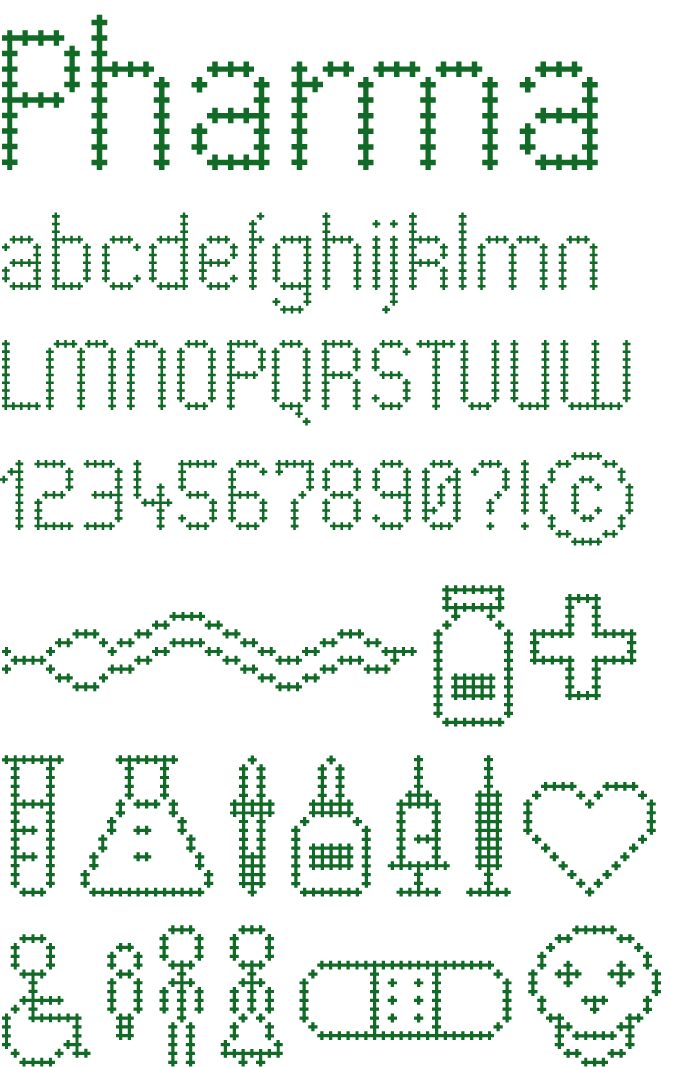
PharmaCare, von Gilles Pegel, ist eine kostenlose Display-Schrift, deren Lettern auf einem präzisen Raster aus winzigen Pluszeichen aufbauen. Diese wiederkehrenden medizinischen Symbole verleihen der Schrift einen sachlichen, modularen Rhythmus, während die simplen Kleinbuchstaben sie eher in Richtung Signaletik und Beschriftung lenken als in den Bereich der dekorativen Schriften.
Sie funktioniert überall dort, wo eine unmittelbare Assoziation zum Gesundheitswesen gefragt ist: Apotheken-Branding, Klinik-Poster, Verpackungs-Mockups, Wellness-Flyer und App-Startbildschirme passen perfekt zu dieser Schrift. Nutzen Sie sie für kurze Überschriften, Regalbeschriftungen oder Titelkarten, bei denen die kreuzförmige Konstruktion die Botschaft vermittelt, noch bevor zusätzliche Grafikelemente ins Spiel kommen.
PharmaCare ist eine pixelartige Schrift auf Basis medizinischer Kreuze.
Sie wird zusammen mit der Piktogramm-Schrift Pharmapicto geliefert, die 28 medizinische Symbole enthält.